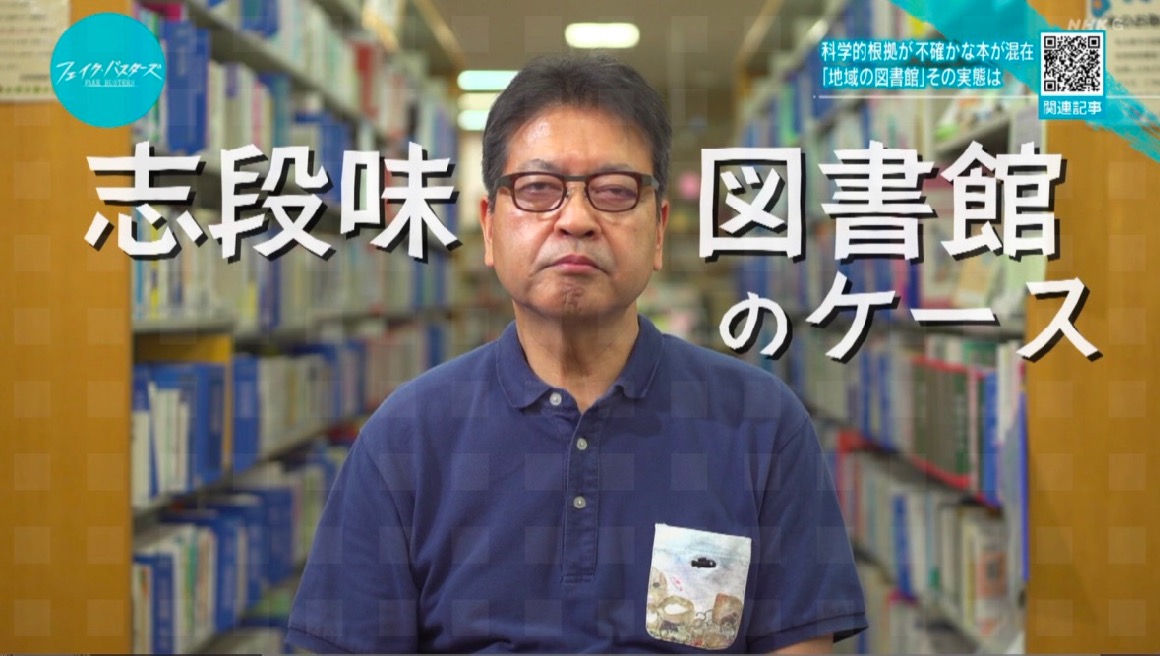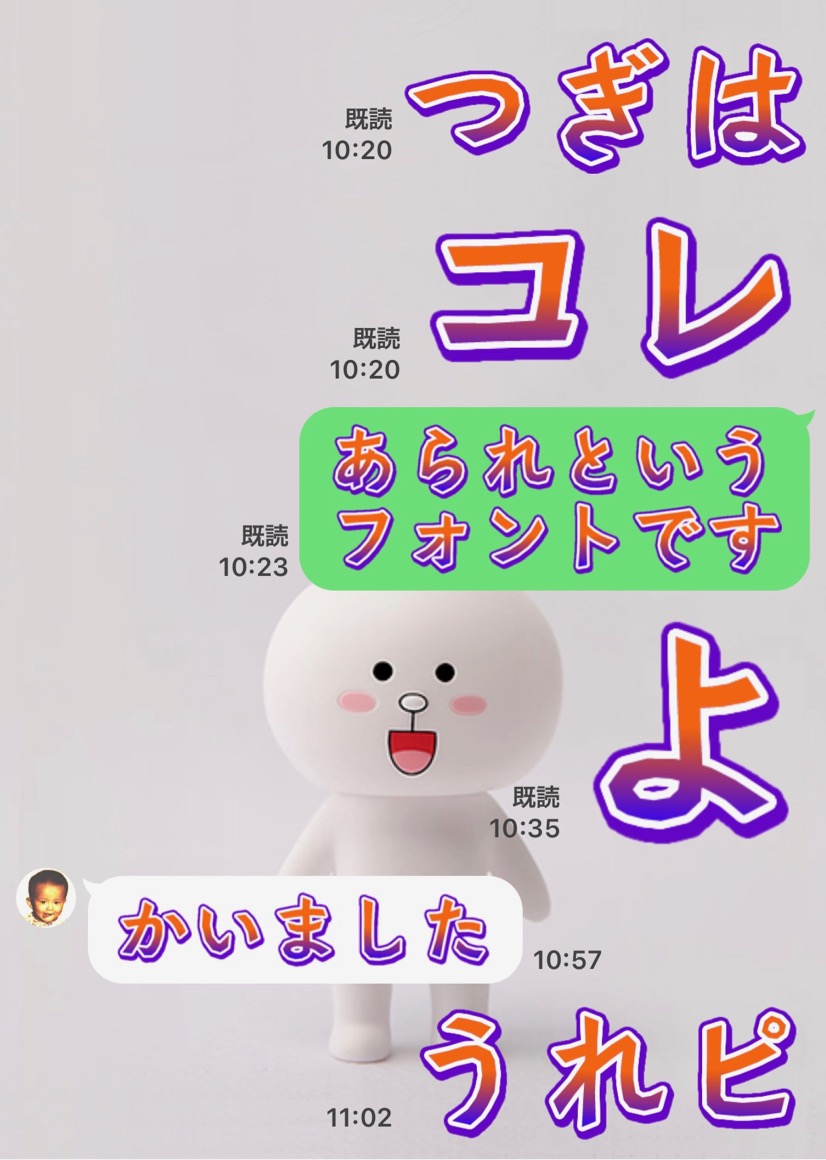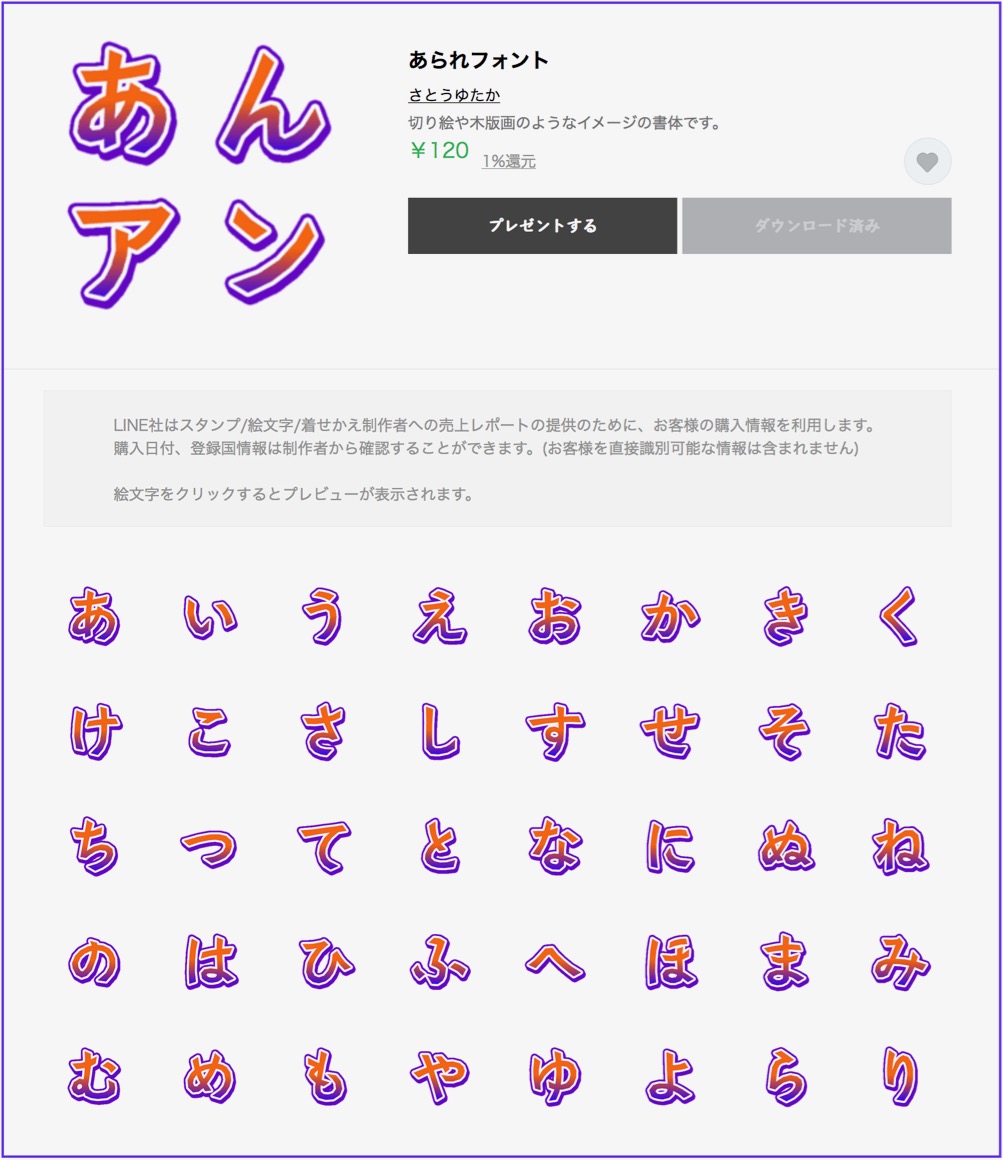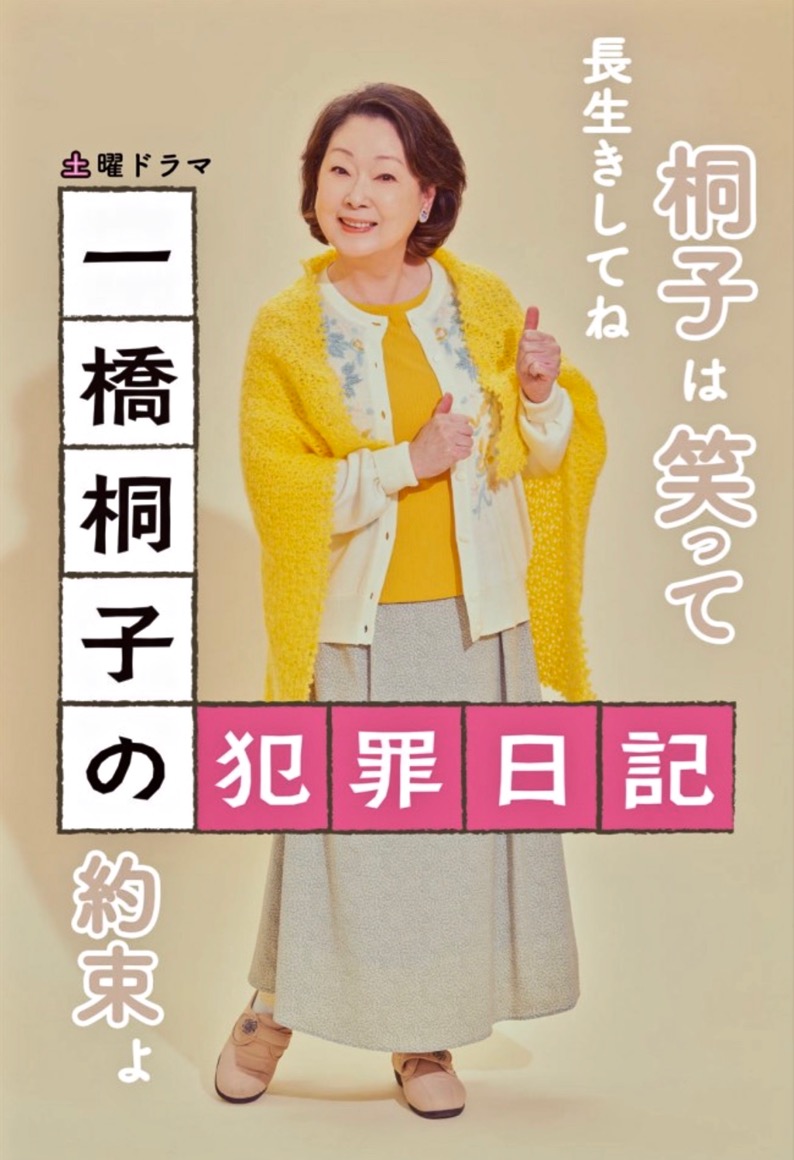
アドビフォントで   さとうゆたか  2024年4月10日(水) 10:24
数日前から、AdobeFontsで使えるようになりました。
和菓子のロゴ  さとうゆたか  2024年3月15日(金) 16:17
四万十川の恵を受けて育った四万十産の栗を使った菓子。
パッケージ。
新型コロナワクチンの治験に関するページ。
画像に「あられ」が使われています。
コンビニで売っていたカップ麺  takumi  2023年11月24日(金) 17:42  HP
コンビニで売っていたカップ麺のパッケージです。
商品名「淡路島産たまねぎカレーうどん」と、その右下の「温暖な〜コク・甘さ」にもあられフォントが使われていますが、少し太らせているようですね…。
フォントが使われている部分を拡大。
パッケージ側面にも。
細いウェイトのものを太らせていますね…。
そのせいで「島」という文字は、作者から見ると黒く不自然に感じます…。
ゲーム実況?  さとうゆたか  2023年10月25日(水) 15:06
クトゥルフ神話trpgのプレイキャラクター紹介かな?
どちらもネット上で拾ったもの…。
あられNが…  さとうゆたか  2023年9月11日(月) 9:41
あられNが…近日中に頒布開始されます。
字種が増えて、太いウェイトもできました。
あられN 太字  さとうゆたか  2023年9月12日(火) 8:55 [修正]
これは、太字です。
縦組みサンプル。
横組みサンプル。
あられN   さとうゆたか  2023年9月12日(火) 9:01 [修正]
これまでと同じ太さのもの。
縦組みサンプル。
横組みサンプル。
購入しました  手羽先  2023年9月12日(火) 13:10  HP [修正]
旧版と比較すると、これまでと同じ太さのものでも濁点が大きくなっていたり、細かなところが調整されていますね!
いちおう「N」となってますから、濁点の大きさとか見直しました…。
細かいところに気づいていただけて嬉しいです。
書体見本  さとうゆたか  2023年8月24日(木) 21:36
フォントワークス社のツイッター(X)に掲載されたもの。
テレビ番組のサムネール  さとうゆたか  2023年8月15日(火) 15:26
2023年8月4日にNHKで放送された
「四国アップデート委員会 夏休みだよ若者集合!」
これも…。
中京テレビの番組  takumi  2023年7月19日(水) 22:51  HP
中京テレビで放送されている「笑える!あなたの地元のプチ不満 土曜日は焼きそば」という番組内であられフォントが使われているようです。
ウチの地域では見られませんが、動画配信サイトで配信されていました。
最後にこれも。
↑これですね。
ページの下の方を見たら、わんぱくルイカとかも使われてました〜。
テレビ番組  さとうゆたか  2023年7月13日(木) 21:33
NHK Eテレで、月に一度放送されている番組「漂流兄妹」。
あ  さとうゆたか  2023年7月13日(木) 21:35 [修正]
けっこう大きく使われている。
これはオープニングだったかな…。